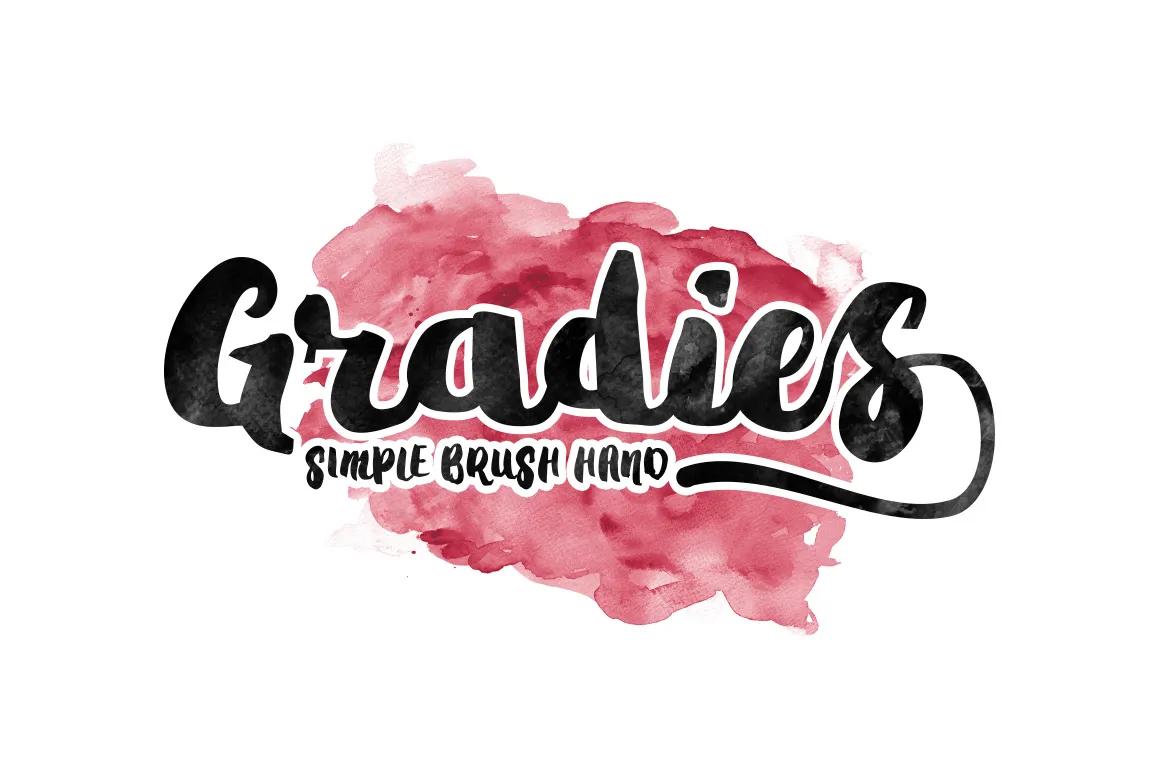
Gradies Brush Font – Download Grátis
A Gradies Brush é uma nova abordagem fresca e moderna para os tipos de desenhos a esfumar, com traços que se enxergam como um estilo de escrita folheada decorativa. Seu caráter é tanto lindo quanto autêntico, especialmente quando usados em cartões de convite ou cartas de cumprimentos, materiais de marca, cartões de negócios, frases ou até mesmo em posters. A Gradies Brush carrega uma leveza na sua escrita que flutua sobre o papel sem perder a consistência necessária, tornando-a ideal para qualquer aplicação visual criativa. A fonte Hamilton traz vida ao seu design através da sua base de letra dançante. Esta característica permite que as palavras deslizem e se movam dentro dos cartões ou imagens do qual são integradas, proporcionando um touch especial de originalidade que torna a Gradies Brush uma escolha perfeita para qualquer uso. Seja você designer gráfico ou editor de texto, a Gradies Brush é uma fonte indispensável que não apenas oferece beleza visual, mas também adiciona uma pitada única ao seu trabalho, tornando-a ainda mais especial e memorable.